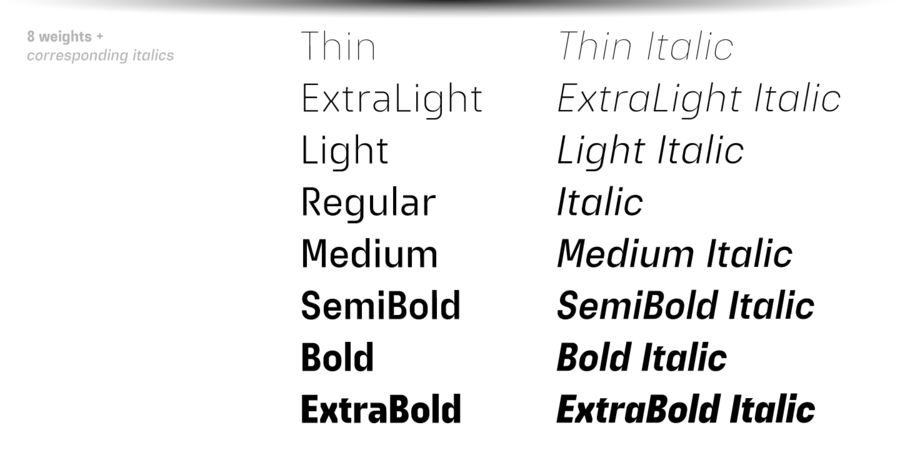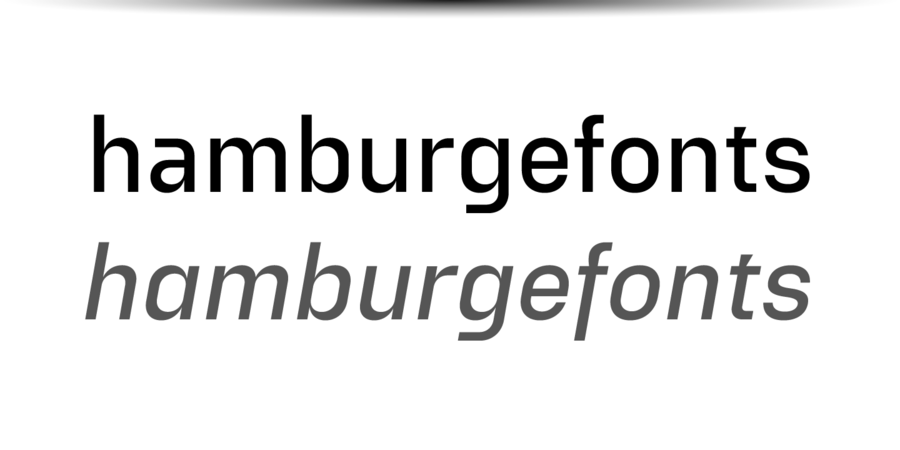
Опис гарнітури ExtaticaЦе еклектичний геометричний акцидентний гротеск з вузькими прописними літерами. Він складається з 8 насиченостей з відповідними курсивними накресленнями, доповнений кількома стилістичними альтернативами та функціями OpenType. Набір гліфів включає всі європейські мови на основі латинки, а також основні мови, що використовують кирилицю. Незважаючи на те, що Extatica створена як акцидентне сімейство, вона також добре працює з невеликими текстами, що робить її ідеальною для стилізованих підписів і підзаголовків. Гарнітуру розробив Андрій Константинов в студії Mint Type у 2021 році.
Асоціації з сімейством шрифтів ExtaticaОсобистість і характер гарнітури:
точний, рівний, прямокутний, стійкий, статичний, міський, прозорий, лаконічний, тонкий, холодний, мінімалістичний, скляний, гострий, крихкий, дротяний, худий, різкий, ламаний, оригінальний, характерний, цікавий, стабільний, техногенний, урбаністичний, переконливий, твердий, серйозний, впевнений, сильний, індустріальний, авторитетний, автоматичний, сталевий, сучасний, логічний, штучний, машинний, інженерний, мотивуючий, залізничний, креслярський, робочий, залізний, крутий, амбітний, архітектурний, грубий, брутальний, важливий, військовий, важкий, суворий, кристалічний, прямий, армійський, екстремальний
техніка, прилад, архітектура, наука, Місто, технології, дизайн, урбаністика, гаджет, девайс, верстат, інструмент, айтішник, IT, айті, завод, інженер, автоматика, космос, промисловість, електростанція, енергетика, ракета, супутник, машинобудування, порт, конструктор, страйкбол, будівництво, вагон, креслення, залізниця, рентген, астрономія, тренажери, ремонт, армія, зброя, архітектор, селфі, вантажівка, далекобійник, сталевар, мотор, двигун, нафта, кристал, код, тара, екстрим, шолом Гарнітура асоціюється з віком: